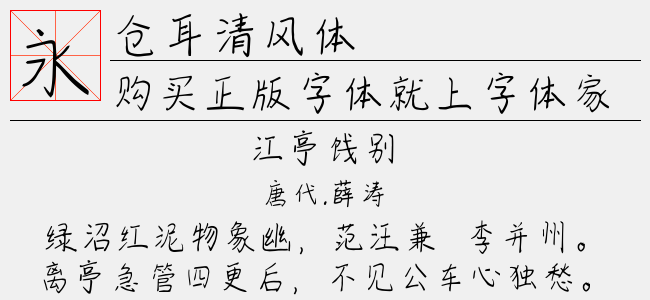
仓耳清风体
字体作者:仓耳字库
字体名称:仓耳清风体
字体家族:仓耳系列
书体类型:手写体
字体公司:仓耳字库
字体设计:仓耳签约设计师
作者职业:设计师
类型:书法
风格:硬笔手写,美术字体,单线超细
这是一款以楷体结构为基础,融入了书写特点的一款手写字体。字体的中宫较为紧凑,端庄大方、运笔自然流畅,结构清晰易识读,清清爽爽,如风儿佛过。适用于各类散文、随笔以及部分产品说明介绍等场景。
仓耳清风体 - 六州歌头(寄孙竹湖)
仓耳清风体 - 晚秋潼关西门作
仓耳清风体 - 过申州作
仓耳清风体 - 大写字母/小写字母/数字